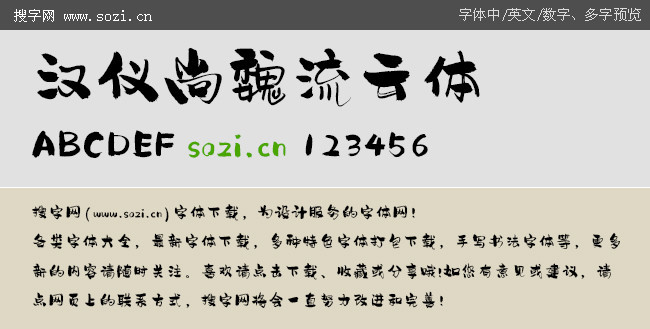
漢儀尚巍流云體
搜字網(wǎng)給大家提供一款漢儀尚巍流云體中文字體下載,漢儀尚巍流云體字型巍峨挺拔,筆畫蒼勁有力,整體效果非常出色,適合應(yīng)用于藝術(shù)設(shè)計(jì)、平面宣傳設(shè)計(jì)、網(wǎng)頁設(shè)計(jì)等應(yīng)用。(本字體為個(gè)人非商用版,如需要商用請聯(lián)系漢儀公司購買版權(quán))